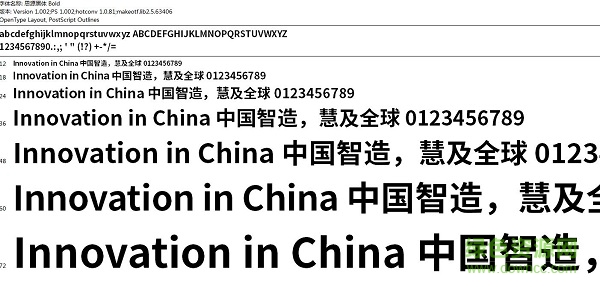
sourcehansanssc bold gbpc euc h字體又叫思源黑體bold,是一款粗體的黑體字體,可以廣泛用于平面設(shè)計(jì)、雜志、期刊、網(wǎng)頁設(shè)計(jì)等領(lǐng)域,需要的朋友快來下載吧!
1.完全支持日文、韓文、繁體中文和簡(jiǎn)體中文。
2.筆形方頭方尾、黑白均勻。
3.可用于手機(jī)、平板、或者桌面的用戶界面、網(wǎng)頁瀏覽或者電子書閱讀等等。